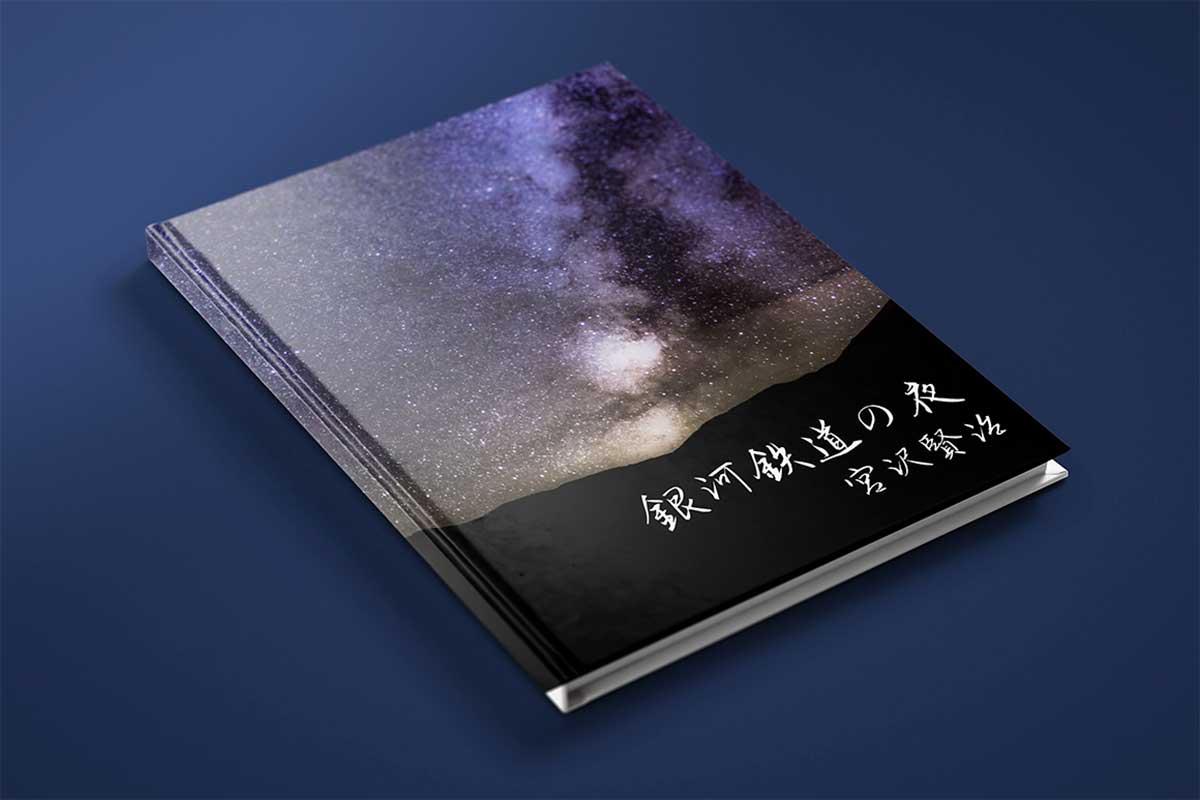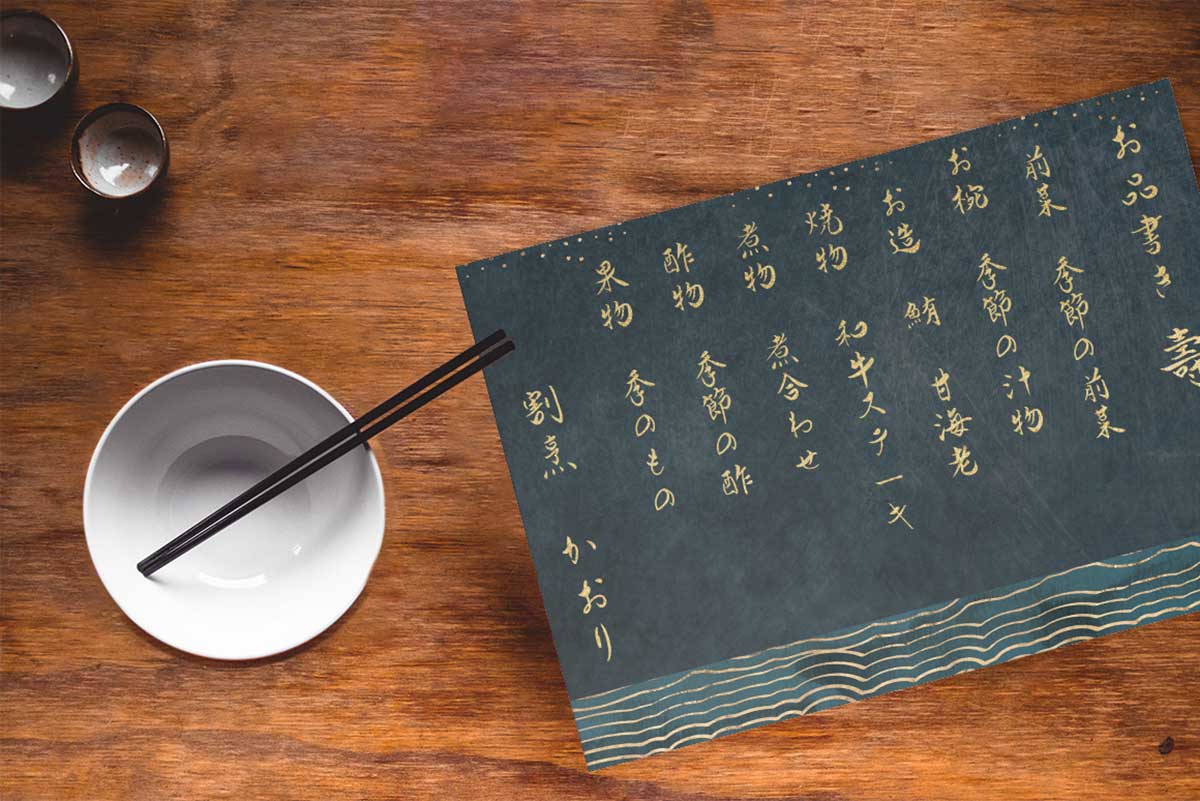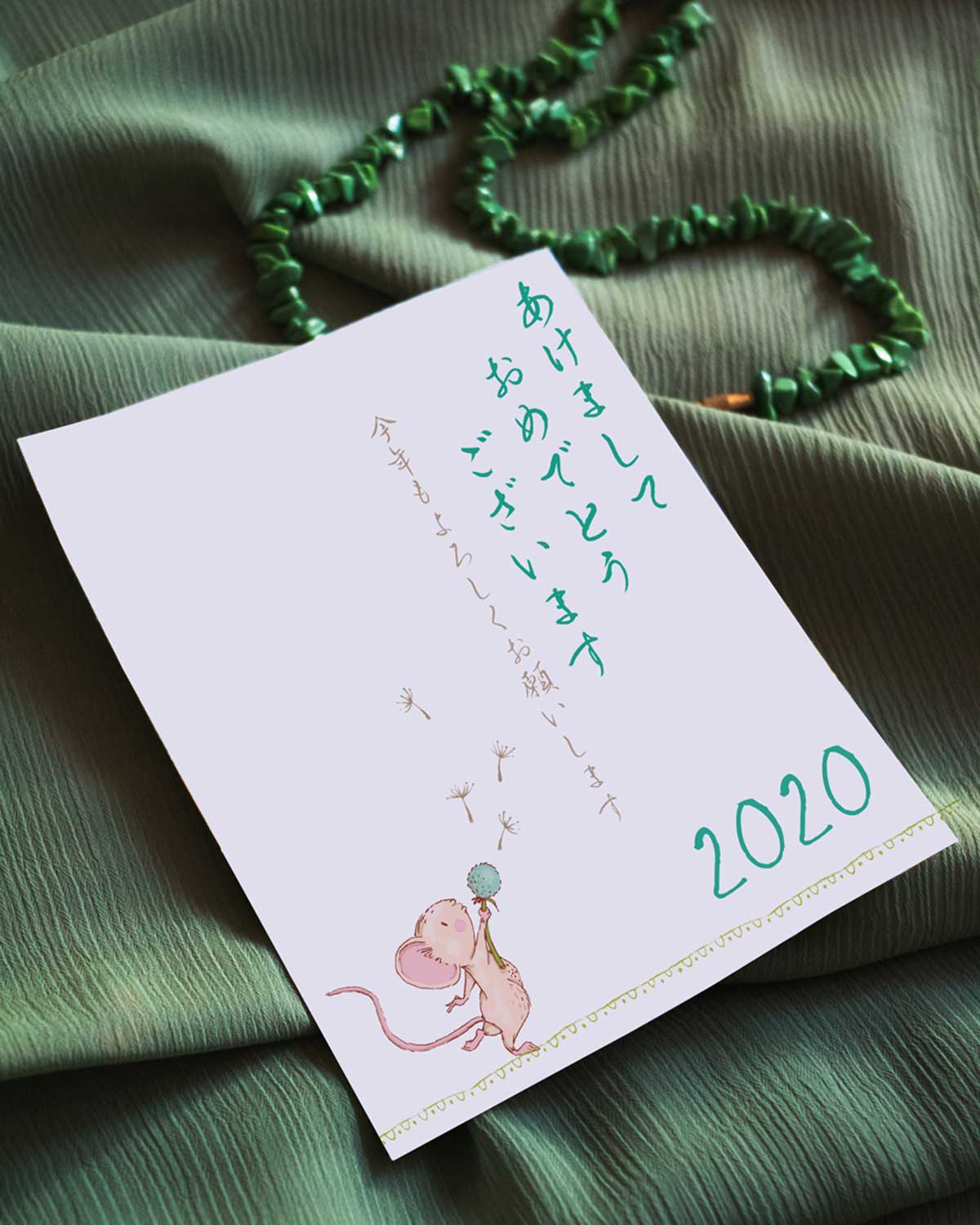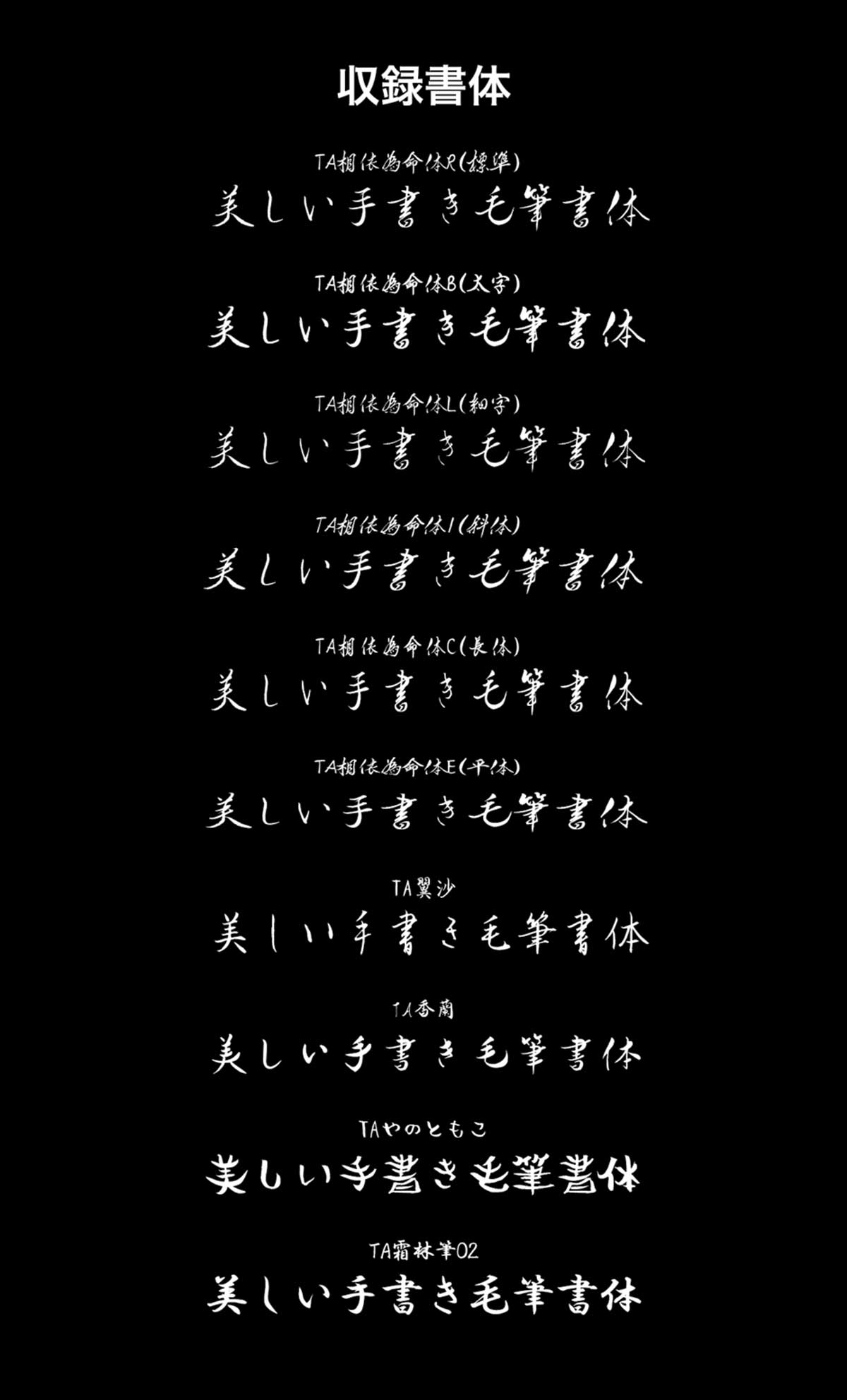
「雰囲気たっぷり毛筆フォント集」の気になる中身
相依為命書体はラストエンペラー愛新覚羅溥儀の実弟「溥傑」の自筆をベースにした、上品で達筆な筆跡のフォントです。
- TA相依為命体R(標準)
- TA相依為命体B(太字)
- TA相依為命体L(細字)
- TA相依為命体I(斜体)
- TA相依為命体C(長体)
- TA相依為命体E(平体)
- TA翼沙
- TA香蘭
- TAやのともこ
- TA霜林筆02